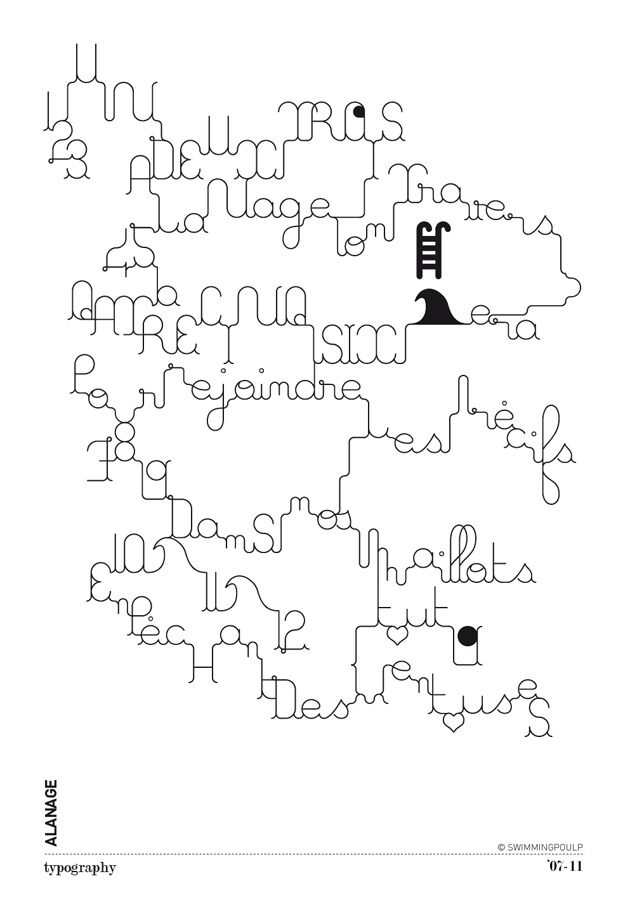
A La Nage Bold, di Swimmingpoulp, è un carattere display gratuito, sinuoso e con un tocco giocoso in stile Art Nouveau. Le lettere scorrono in tratti spessi e arrotondati che si intrecciano come un nastro continuo, conferendo al carattere un ritmo fluido e quasi liquido, lontano dalla rigidità dei titoli classici.
È perfetto per poster, copertine di album, branding per bar, titoli di libri per bambini e packaging in cui un'atmosfera rétro morbida conta più delle linee dritte. Trattandosi di un font gratuito, è ideale anche per loghi brevi, titoli e citazioni in evidenza, poiché quei lunghi intrecci e quelle curve bulbose donano a ogni parola una silhouette distintiva e leggermente stravagante.